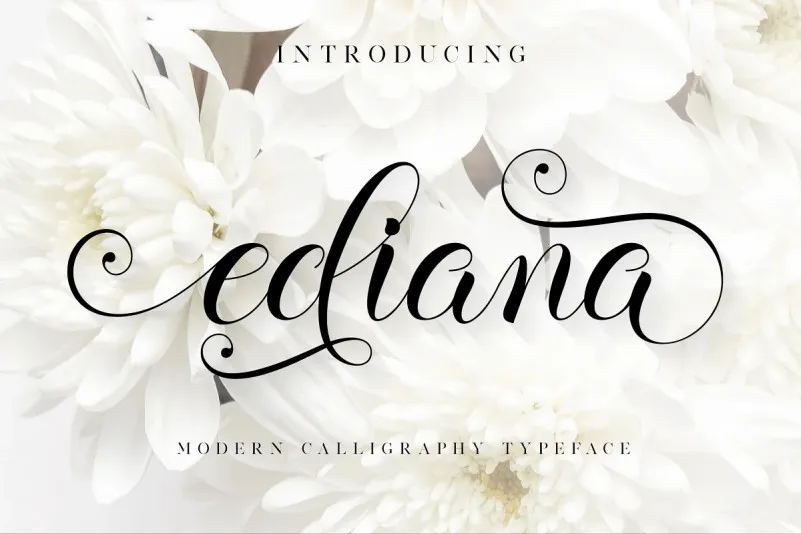
A Ediana Font é uma elegante fonte moderna à mão escrita criada por fanastudio. Ela oferece uma completa gama de letras maiúsculas e minúsculas, símbolos multilíngues, números e pontuação. O que torna esta fonte especial é seu uso exclusivo de ligaduras para dar um toque sofisticado a seus projetos de arte pessoais. A Ediana Script é perfeita para diversas finalidades, incluindo logotipos e marcações, convites, materiais de embalagem, designs de casamentos, postagens nas redes sociais, publicidade, embalagens de produtos, etiquetas, fotografia, marcas água e eventos especiais. A fonte traz um toque autêntico e elegante ao seu trabalho, tornando-a perfeita para qualquer projeto que necessite de uma pitada de escrita à mão.